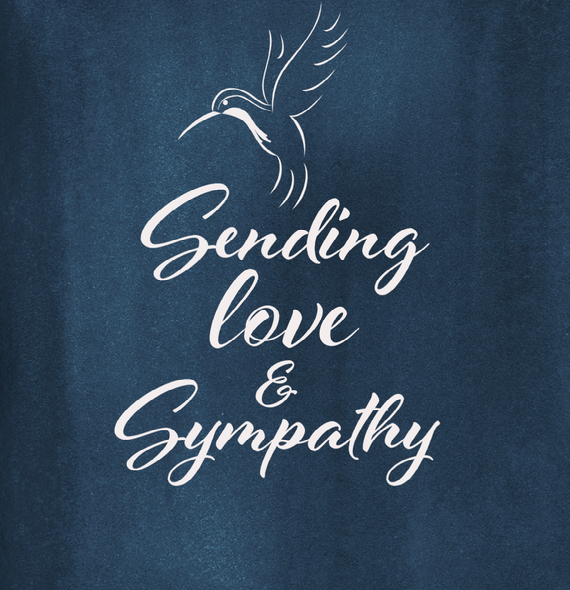
Font MTD ALFresco Việt Hóa
Font MTD ALFresco là một chữ thuộc bộ font MTD, sở hữu sự độc đáo với phong cách viết tay phóng khoáng, font MTD ALFresco mang đến cảm giác tự nhiên và thoải mái. Đặc trưng của font này là các đường nét mềm mại, không quá gò bó, giúp nó trở nên phù hợp cho các thiết kế liên quan đến ẩm thực, nhà hàng, hoặc các dự án sáng tạo cần sự tươi mới và thân thiện. Font MTD ALFresco đặc biệt lý tưởng cho các thiết kế logo, tiêu đề, bao bì hoặc các ấn phẩm đòi hỏi sự sinh động và cá tính, mang lại cảm giác gần gũi và ấn tượng cho người xem.